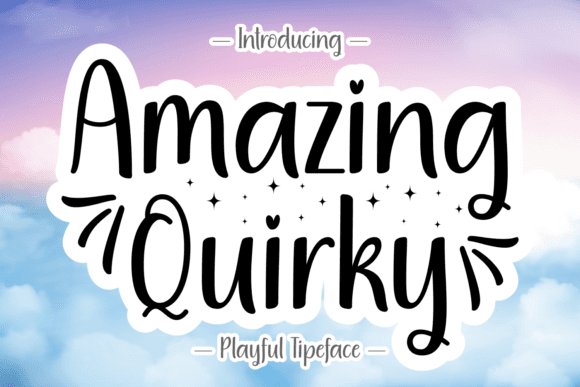
Fuente original e increíble para manualidades, logotipos y proyectos de impresión.
Amazing Quirky es una tipografía divertida y expresiva que aporta un toque desenfadado a logotipos, proyectos de manualidades y medios impresos. Sus formas irregulares y su alegre estilo la hacen ideal para branding y diseños artesanales.
Esta fuente está diseñada para brindar energía visual y creatividad. Funciona a la perfección en formatos digitales y físicos, ayudándote a crear diseños impactantes con personalidad y singularidad.
Desde etiquetas de boutique hasta carteles para aulas, Amazing Quirky hace que cada diseño sea un poco más memorable.
Por qué te encantará
- Estilo caprichoso con encanto hecho a mano.
- Perfecto para manualidades, marcas y señalización.
- Carácter visual memorable en cada uso.
P: ¿Qué estilo de fuente es Amazing Quirky?
R: Es una fuente de visualización divertida y peculiar, ideal para manualidades, logotipos y materiales impresos.